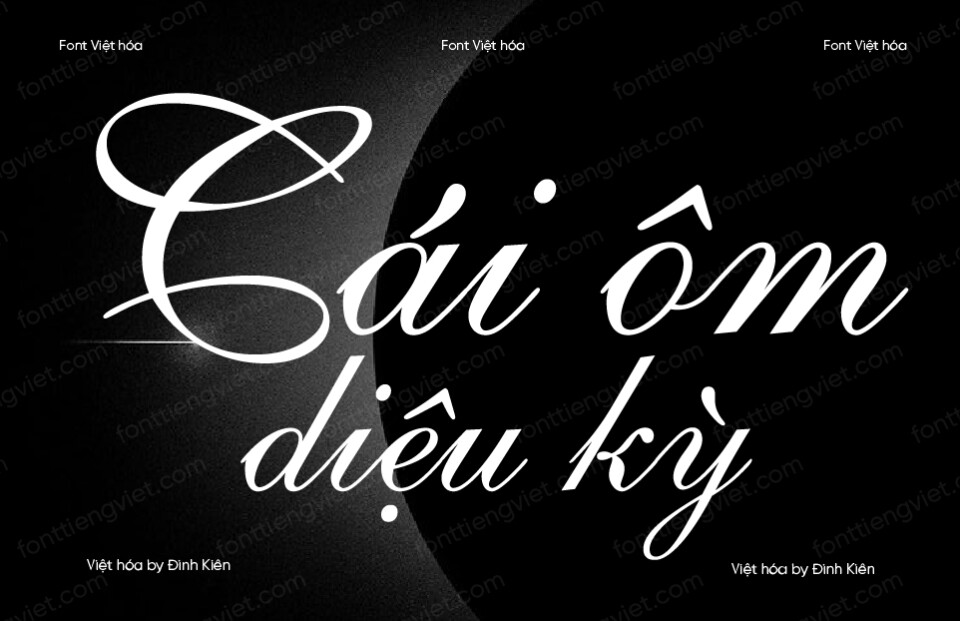
Giới thiệu về Font Việt hóa UTM Father
Trong thế giới đồ họa, việc lựa chọn một Font Chữ phù hợp đóng vai trò quan trọng để truyền tải thông điệp hiệu quả. Font Việt hóa UTM Father là một trong những bộ phông chữ thuộc hệ thống UTM nổi tiếng, được tinh chỉnh hoàn hảo để tương thích với bảng mã Unicode. Đây là lựa chọn lý tưởng cho các bạn học sinh, sinh viên và giáo viên khi cần tạo ra các bài thuyết trình hay tài liệu học tập có tính thẩm mỹ cao mà không lo lỗi font tiếng Việt.
Đặc điểm nổi bật của bộ font này
Cấu trúc của Font Việt hóa UTM Father mang phong cách mạnh mẽ nhưng vẫn giữ được nét tinh tế, hiện đại. Các đường nét được thiết kế dứt khoát, giúp văn bản trở nên dễ đọc và bắt mắt. Đặc biệt, font này cực kỳ linh hoạt, phù hợp cho cả mục đích thiết kế tiêu đề trang trọng lẫn nội dung trang trí sáng tạo trong môi trường học đường.
Cách ứng dụng Font Việt hóa UTM Father hiệu quả
Sử dụng trong giáo dục và đồ họa
Giáo viên có thể sử dụng Font Việt hóa UTM Father để thiết kế bằng khen, thiệp mời hoặc các tiêu đề bài giảng điện tử sinh động. Đối với học sinh, bộ font giúp các bạn làm nổi bật các dự án cá nhân hoặc báo cáo nhóm. Việc cài đặt cũng rất đơn giản, chỉ cần tải về, giải nén và đưa vào thư mục font của máy tính là có thể sử dụng ngay trên Microsoft Word, PowerPoint hay Photoshop.
Kết luận về bộ font chất lượng